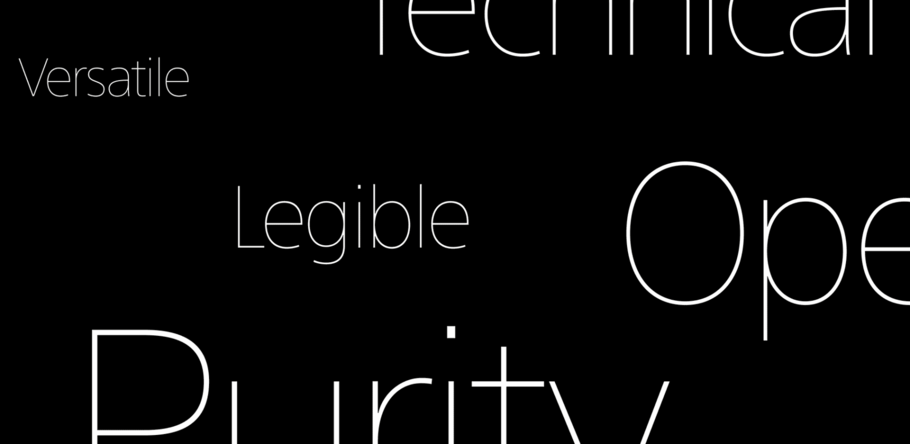
Une police, 93 langues : le défi d’une création pour Sony.
“ Il y a beaucoup d’avantages à avoir créé SST, mais le plus considérable est qu’à présent, une superbe police existe pour couvrir à elle seule une expérience utilisateur cohérente à travers le monde entier et sur n’importe quel appareil. ”
Designers
Le directeur typographe Akira Kobayashi a étroitement collaboré avec le directeur artistique en chef de Sony, Hiroshige Fukuhara, pour créer une police originale couvrant une centaine de langues environ, diverses interactions client et des décennies d’utilisation.
Sony s’est rapproché de Monotype avec une vision audacieuse et sans complexe pour un design de police originale qui serait opérationnelle sur ses produits, dans les magasins, en ligne et essentiellement dans chacun de ses points de contact client à travers le monde - des clients qui communiquent dans 93 langues, rien de moins. Après avoir obtenu une connaissance parfaite de la liste de souhaits de Sony pour sa police SST®, le directeur typographe de Monotype Akira Kobayashi admet ressentir « le poids de la responsabilité d’un projet qui allait contribuer à construire l’image de marque de Sony… Aujourd’hui, ça me fait sourire quand je me rappelle combien ce projet complexe semblait intimidant. »
Dans son blog, la société multinationale assure qu’elle était persuadée que Monotype était à la hauteur de la tâche, grâce à sa compréhension de l’histoire typographique et de ses idéaux, à sa propre ancienneté au sein de cette histoire, grâce à son expertise dans le développement multilingue et bien sûr à son solide soutien qui allait du design typographique à l’optimisation de l’affichage. « Les polices sont des éléments clés du design, elles façonnent notre idée du produit et l’expérience de l’utilisateur en soi, » affirme Sony.
Le défi
Le directeur artistique en chef de Sony, Hiroshige Fukuhara, explique : « Mon inspiration initiale avait été de créer une police authentique, une chose qui me passionnait. Tous les membres du projet partageaient mon égard pour l’authenticité. Nous étions à la recherche d’une police originale, fondée sur de solides traditions typographiques. Nous espérions qu’elle résisterait à des dizaines d’années à venir. Et le développement multilingue était prévu depuis le début.
“ Les polices sont des éléments clé du design, elles façonnent notre idée du produit et l’expérience de l’utilisateur en soi. ”
Se servant des polices Frutiger® et Helvetica® comme points de départ, la police SST® de Sony est une sorte d’hybride issue de ses deux polices, elle associe la lisibilité naturelle de Frutiger à la géométrie pointue de Helvetica. Avant tout, cette police spécialement créée pour Sony devait être facile à utiliser et permettre de profiter du contenu de la marque dans le monde entier. Parmi les autres exigences, il fallait que la police soit lisible même en petite taille, discrète, solide, aiguisée, technique, pure, indémodable et polyvalente - fonctionnant aussi bien sur un smartphone que sur un panneau d’affichage. Elle ne pouvait pas non plus être trop différente de Helvetica, la police auparavant utilisée par Sony en de maintes occasions.
La police de caractères SST de Sony marie la lisibilité organique de Frutiger et la géométrie pointue de l’Helvetica.
« Nous avons compris que la police devait rester en retrait et ne pas trop en faire » raconte Kobayashi. « De manière idéale, elle rassemblerait une palette d’éléments - des qualités dures et tendres, un sens d’identification du produit, des proportions naturelles, etc. Pour cette raison, il s’agit d’un compliment de dire qu’aucun trait ne sort de l’ordinaire, si nous comparons les fonctionnalités des caractères individuels à celles d’autres polices. Peu de personnes dans un magasin seraient probablement en mesure de se rendre compte que la police sur les emballages de Sony est différente. À cet égard, je pense que nous avons adopté une approche très naturelle pour nous assurer que la police allait correspondre à l’image des produits Sony. »
La solution
Le même souci du détail apporté par Sony au développement de ses produits a été appliqué à la mise au point des polices SST. L’épaisseur des lettres est conçue pour paraître constante, même si elle ne l’est pas, jouant sur les illusions d’optique qui influencent la manière dont les caractères apparaissent. Les lignes verticales et horizontales sont d’une épaisseur assez identique, et un grand espace est donné aux ouvertures et aux contre-formes pour maximiser la lisibilité même à des tailles plus petites. Tous les caractères sont de taille égale de sorte qu’un C soit seulement 1,2 fois plus grand qu’un S, par exemple.
Pour unifier une police qui ne prendrait pas seulement en charge l’anglais et le japonais mais aussi le grec, le thaï et l’arabe - 93 langues en tout - Monotype s’est appuyé sur les talents de son réseau local de designers, qui comptaient sur Kobayashi pour obtenir des instructions concernant des détails comme le rayon de courbure ou l’épaisseur de ligne. Littéralement, les idéaux de Sony en matière de police de caractères ont été traduits dans beaucoup de langues. Il s’est révélé particulièrement éprouvant d’unifier une police incluant le langage asiatique ; SST est le premier projet au monde dans le secteur de Sony à y parvenir. Et pourtant, au bout du compte, la police disponible pour un total impressionnant de 93 langues fut créée.
“ Il y a beaucoup d’avantages à avoir créé SST, mais le plus considérable est qu’à présent, une superbe police existe pour couvrir à elle seule une expérience utilisateur cohérente à travers le monde entier et sur n’importe quel appareil. ”
La police SST a déjà été présentée sur le site Web de Sony, sur l’emballage des produits et dans les manuels d’utilisateur. Elle sera bientôt établie en tant que police d’entreprise de Sony et utilisée sur une multitude de produits Sony.
L’équipe Studio.
Akira Kobayashi.
Akira Kobayashi
Akira Kobayashi, directeur typographe, possède trois décennies d’expérience et une connaissance approfondie de la typographie japonaise, ainsi qu’une compréhension approfondie de la calligraphie. Après quatre ans d’études à l’université d’art de Musashino à Tokyo, Akira Kobayashi a commencé par travailler dans l’entreprise de composition photo Sha-Ken Co. où il s’est consacré au processus long et compliqué du design de caractères japonais.